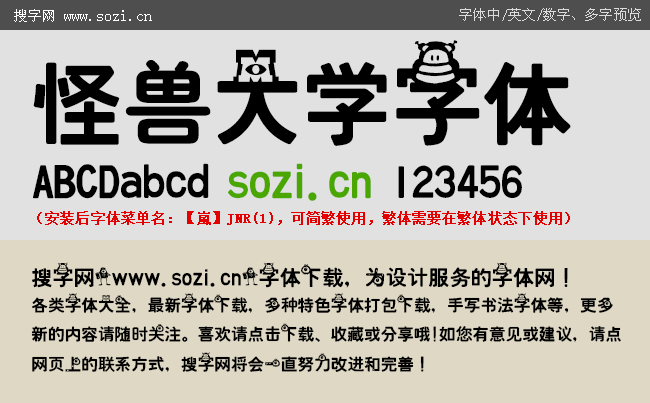
怪獸大學(xué)字體
搜字網(wǎng)給大家提供一款怪獸大學(xué)字體手機(jī)中文字體下載。這款手機(jī)中文字體以粗黑體為原形,字體上加上了卡通卡通小怪獸圖案,該字體即有黑體端正醒目、易認(rèn)的特點(diǎn),又增添了一些趣味性,非常適合喜歡個(gè)性的朋友在手機(jī)上安裝使用。